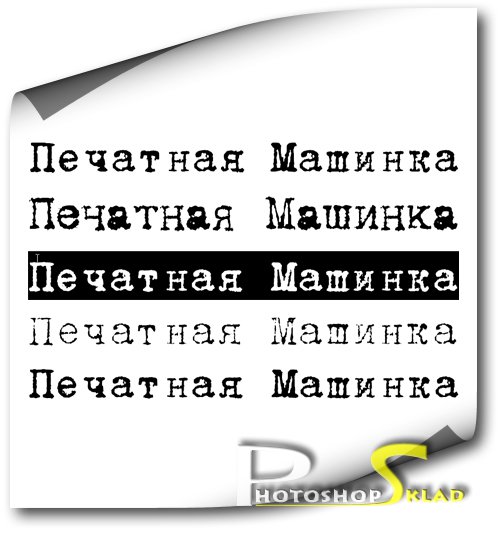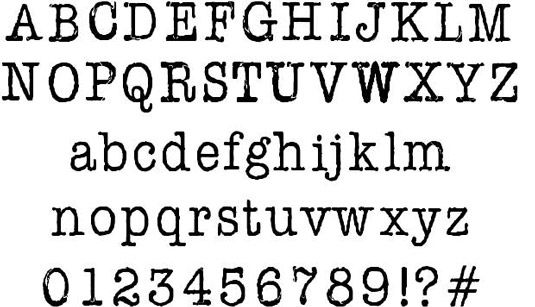
Акцидентные
К этой группе относятся шрифты, не укладывающиеся в предыдущие группы классификации, а также специально предназначенные для акцидентного набора и имитирующие определенный исторический стиль или декоративную обработку формы, например, Модерн, Ар Деко, оп-арт, контурные, выворотные, трехмерные, фактурные, орнаментальные, трафаретные, машинописные, экранные, с рваным контуром и т.д.
Акцидентные шрифты, сохраняющие привычный рисунок и укладывающиеся в рамки классификации, принятой для текстовых шрифтов. Шрифты для очень крупных кеглей, крайние варианты шрифтов привычного рисунка.
- ITC FatFace
Экстремальные шрифты делятся на:
-
Сверхжирные
-
Сверхтонкие
-
Сверхширокие
-
Сверхузкие
-
Сверхконтрастные
Геометрические
Собранные из простых геометрических форм и лишь условно напоминающие знаки традиционной формы.
Экспериментальные
Акцидентные шрифты, резко отличающиеся по форме знаков, шрифты с измененным контуром знаков, измененной формой знаков, гибридные, «живые» шрифты и др.
Нарушения контура
Акцидентные шрифты или начертания с измененным контуром знаков (грубым, рваным, имитирующим оттиск на шероховатой бумаге и т.д.).
- Academy Rough
- AdverGothic Rough
- Bernhard Rough
- Compakt Rough
- Compakt Wind
- Courier Rough
- Crash
- Guenter
- Hermes Rough
- Mistica
- Nazhdak
- Ottisk
- Wind
Нарушения формы
Акцидентные шрифты, резко отличающиеся по форме знаков, с измененной формой знаков или их деталей, гибридные – составленные из знаков разных гарнитур или имеющие знаки, склеенные из нескольких частей от разных гарнитур, и т.д.
- Bistro
- Compakt Broken
- Compakt Dance
- Cracker
- Dead History Cyrillic
- Dikovina
- Drunk
- Duetto
- FaRer
- Garbage
- Garbedge
- Graffiti
- Gulitov
- HotSauce
- KvadratZ
- MonoCondensed Zoom
- Monte Summa
- Musor
- Pollock
- Probbarius
- Quartet Cyrillic
- Shaltai
- Somaton
- Strelochnik
Имитации
Основанные на реально существующем или существовавшем способе построения и/или воспроизведения знаков.
Деревянные литеры
Машинописные
Акцидентные и текстовые шрифты, по форме имитирующие шрифт пишущей машинки, а также любые шрифты с одинаковыми ширинами знаков. Моноширинные шрифты применяются для набора таблиц и технических текстов, а машинописные для имитации машинописного текста и для акциденции.
1 / 100- Courier
- Courier (APC)
- Courier Monotonic Greek
- Courier Polytonic Greek
- Jatran
- MonoCondensed
- Optimus
- Priamoj
- Secretary
- Telegraph
Электронные
Акцидентные шрифты, эксплуатирующие эстетику компьютерных, экранных и других близких по назначению шрифтов.
Шрифты OCR
Акцидентные шрифты, имитирующие форму знаков шрифтов для машинного оптического распознавания, штриховых кодов и т.д.
- Countdown
- OCR One
- Techno28
Экранные
Акцидентные шрифты, имитирующие форму и фактуру знаков экранных шрифтов низкого разрешения.
- Dotage
- Ecyr
- FixSys
- Lo-Res Nine Cyrillic
- Mobul
- Multicross
- AZ Poligon
- Strob
- Tablo
Шрифты табло
Акцидентные шрифты, имитирующие форму и фактуру знаков разнообразных шрифтов для информационных табло, матричных принтеров, жидкокристаллических дисплеев и других устройств, воспроизводящих шрифт с низким разрешением.
- Crystal
- Electronica
- Perfo
- Performance
Трафаретные
Акцидентные шрифты, имитирующие надписи, выполненные по трафарету. Знаки состоят из отдельных элементов, разделенных белыми перемычками. Иногда элементы знаков заполнены различными фактурами.
- Aksent
- Bardi
- Cliche
- Debby
- DJ Parade
- FavoritTraf
- Futura Eugenia
- Glasten
- Mania
- Nelma
- Plain
- Start
- Trafaret
- New Zelek
Натурные
Декорированные
Сюда относятся декоративные шрифты, предназначенные для акциденции, не укладывающиеся в предыдущие группы классификации, форма которых имеет преувеличенные детали или подверглась изменению с целью усиления декоративности.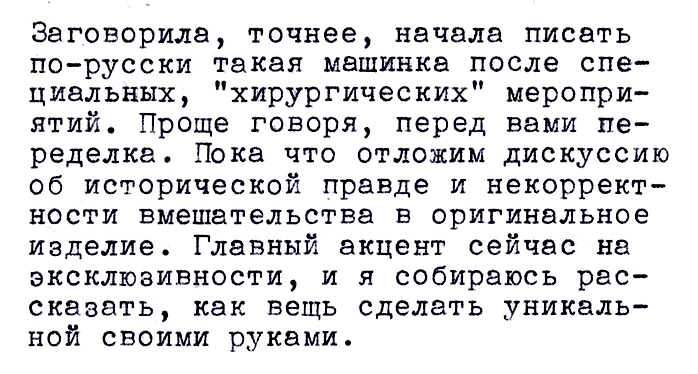
Орнаментированные
- Orbi
Текстурированные
- Wind
Контурные, трехмерные, фактурные и выворотные
Акцидентные шрифты, знаки которых образованы контурами различной толщины, иногда с заполнением внутри, оттенением или и тем и другим. Иногда штрихи таких шрифтов заполнены фактурами или представляют собой негативное изображение.
- AdverGothic Cameo Bold
- Borjomi Decor
- Dotage
- Dynar Shadow
- EdgeLine Shadow
- Europe Shadow
- Futura Futuris Shadow
- Futura Futuris Volume
- Inform Shadow
- Izhitsa Shadow
- Josephine
- Leshy
- Sans Decor
- Tauern
- Template Gothic Cyrillic